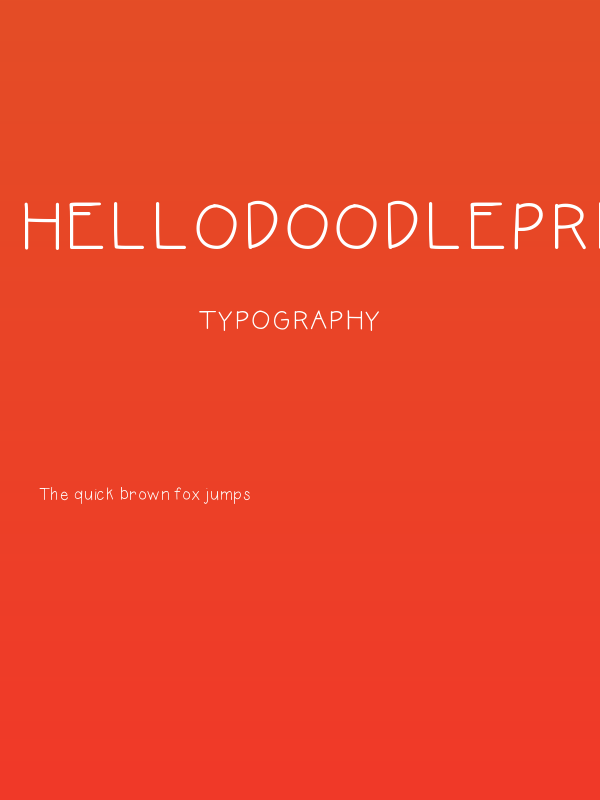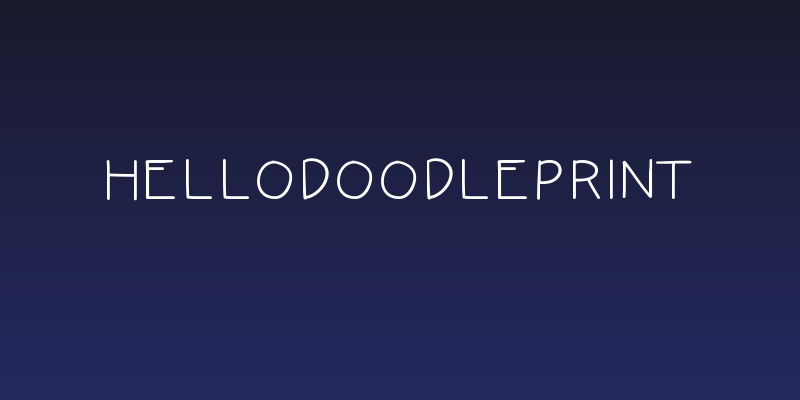
HelloDoodlePrint Font
| Estilo general | Playful |
| Caso de uso | Headlines, Logos, Informal Text |
| Proyectos propuestos | Ideal for children's books, greeting cards, playful branding, and casual invitations. |